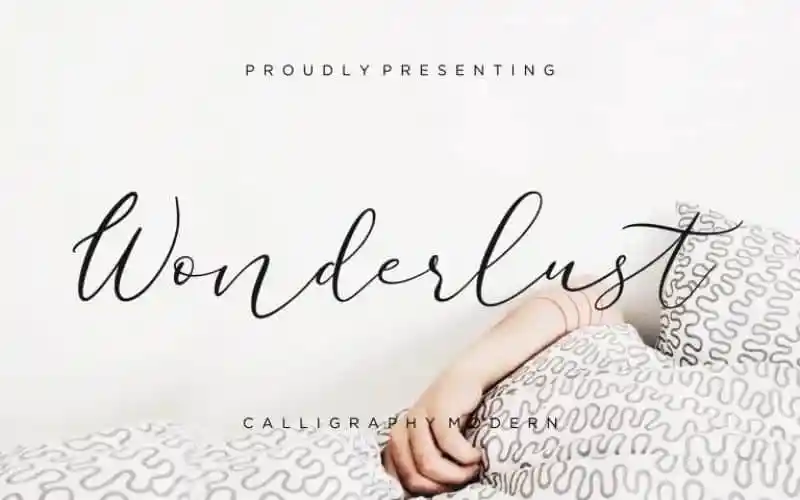
Wonderlust Calligraphy Font – Download Grátis
Wonderlust Calligraphy Font é uma nova e encantadora fonte calligrafia, criada pelo designer Creatype Studio. Com suas bordas naturais, esta fonte transmite um toque autêntico de trabalho artesanal, oferecendo um gosto perfeito para projetos em diversos campos como branding, logomarca, desenho de casamento, posts nas redes sociais, anúncios, embalagens de produtos, design de produto, etiquetas, fotografia e marca d’água. Além disso, é perfeita para invocações, material de estação ou qualquer projeto que precise da delicadeza do traço da mão. Com Wonderlust, você pode dar ao seu projeto um toque único e sofisticado.